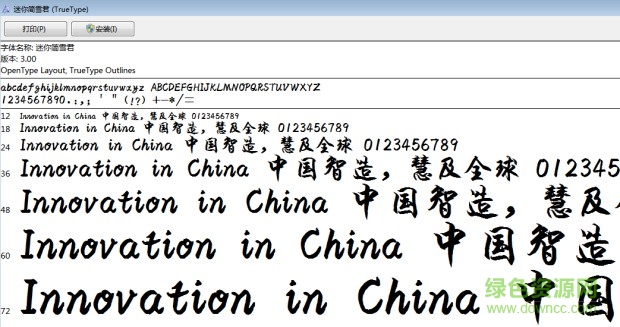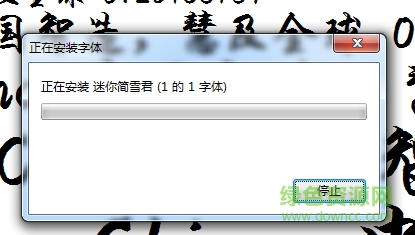
迷你簡(jiǎn)雪君
迷你簡(jiǎn)雪君字體下載是一款非??蓯鄣?a href="http://573ee.cn/k/shoujiziti/" target="_blank">手機(jī)字體這個(gè),這個(gè)字體打印的效果十分的不錯(cuò),而且經(jīng)常能在廣告和海報(bào)設(shè)計(jì)上面見到這款字體,這款字體應(yīng)用非常廣泛,并且還有超多用途,喜歡的就來下載吧!
字體特色
點(diǎn)畫活潑,體勢(shì)清朗,眉目清秀,體態(tài)大方,體現(xiàn)了啟體
點(diǎn)雅遒麗、超邁瀟灑的書法風(fēng)格,具有明快大方的特點(diǎn)。
字體取自“不激不厲,志氣平和”之意境,在結(jié)構(gòu)上富于
變化,在大起大落、跌宕起伏中尋求平穩(wěn),表現(xiàn)出書法字
體的寫意美。宜作廣告字體。
雖然是一款草書風(fēng)格的字體,但盡量保持字體原形,對(duì)筆
劃適當(dāng)減少,做到易學(xué)易識(shí),且融簡(jiǎn)、繁寫法于一體,匠
心私具。可用于文章標(biāo)題、廣告制作、裝飾、裝幀等。